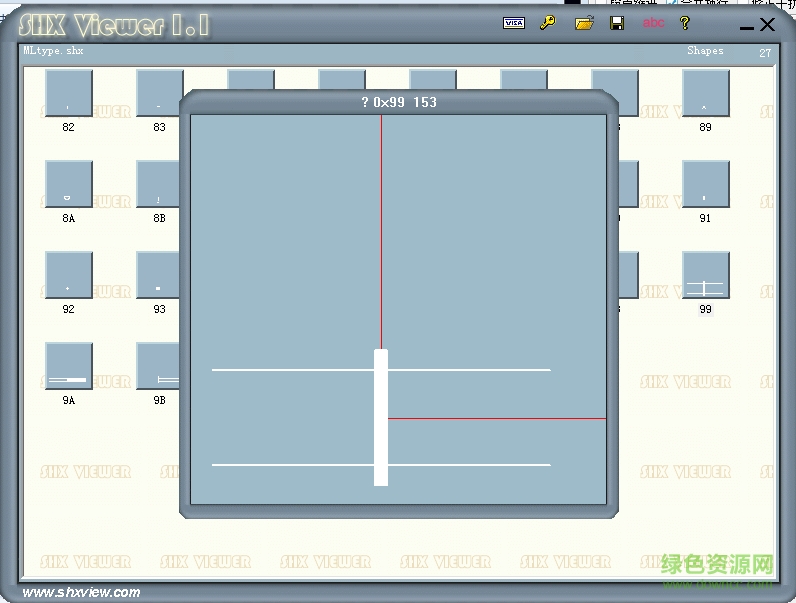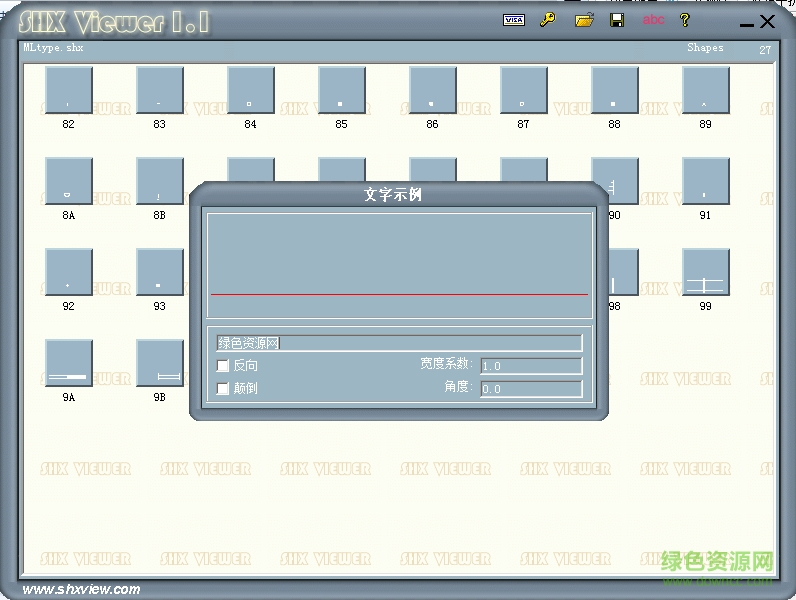
mltype.shx是最近网友好的较多的一款cad字体,有着独特的造型和书写方式,为你的设计增加个性魅力,绿色资源网欢迎大家免费下载体验!
在CAD字体中,字体文件均为SHX格式,mltype.shx就是其中的一款,但部分朋友可能无法使用本字体,原因是字体名称被他人私自修改,如果能正常打开即可放心使用了!